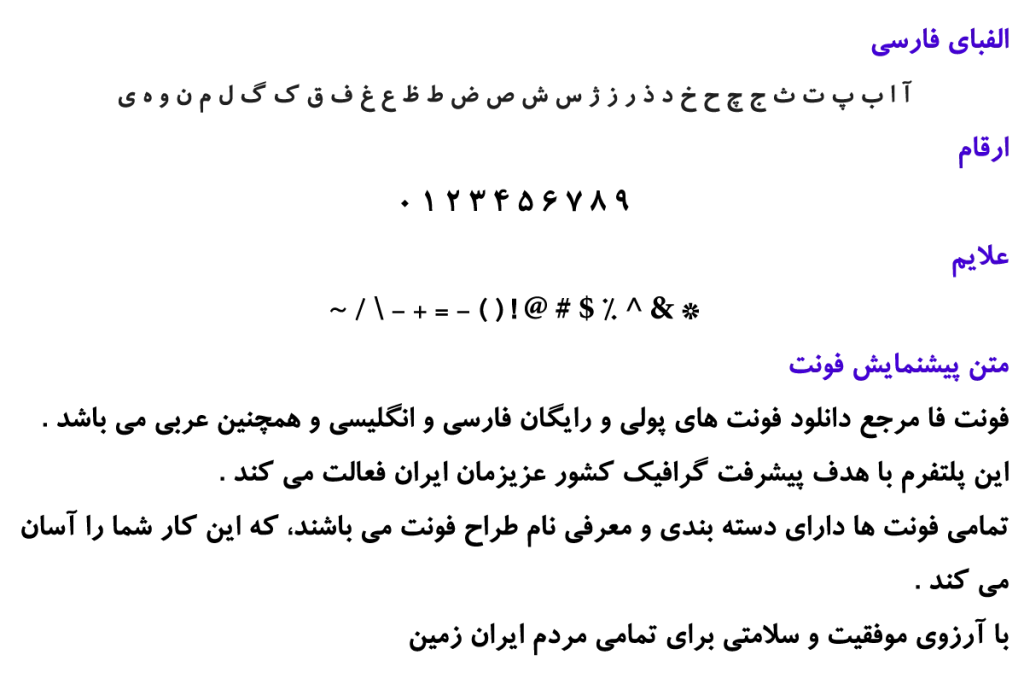
فونت فارسی رویا – B Roya
طراح فونت: برنا رایانه نوع فونت: فونت عنوان و فونت متن
توضیحات و معرفی فونت رویا
فونت فارسی رویا ( B Roya ) از مجموعه فونت های سری B می باشد، همچنین نوع فونت عنوان و متن می باشد.
فونت فوق العاده زیبای معرفی شده توسط برنا رایانه در سال 1379 طراحی و ساخته شده است.
همچنین فونت B Roya در 2 وزن پر رنگ و معمولی است.
در لیست زیر می توانید وزن های این فونت فوق العاده زیبا را ببینید.
- B Roya Bold
- B Roya Regular
نمونه ی تصویری زیر، تایپ فیس را در ترکیب با شعری میهن دوستانه نمایش میدهد.